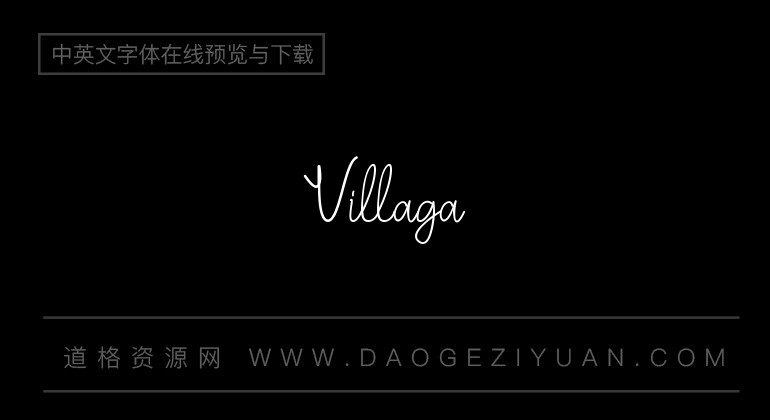
Villaga 字体是一款由葡萄牙设计师 Frederico Silva 创作的字体,它是一种抽象风格的现代字体,具有良好的可读性和美感。Villaga 字体的字形结构简洁、清晰,它的核心特征是圆形的笔画,使得它具有流畅的连续性。Villaga 字体有很强的视觉冲击力,适合用于广告、海报、品牌标识等设计中。内容介绍
Villaga是一款非常不错的手写艺术字体,具有很好的视觉感,适合于文化类的宣传设计、商业类品牌的广告和产品包装设计以及个性化文字排版等较多场景。